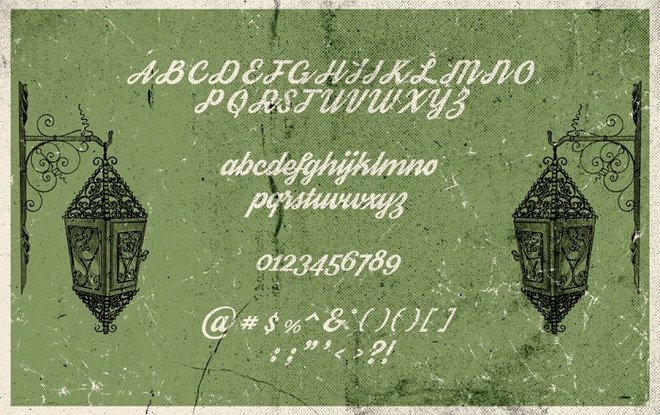
Với một Designer chuyên nghiệp, đây là 9 font chữ chẳng thể bỏ qua
Designer giờ đã trở thành một ngành nghề không còn xa lạ. Tuy nhiên, sở hữu những công cụ tốt - ở đây là font chữ - sẽ giúp các sản phẩm của họ vượt trội hơn so với phần còn lại.
Trong thời đại mọi thứ đều sử dụng công nghệ như ngày nay, việc thiết kế chữ nghệ thuật, tên các nhãn hiệu thời trang bằng máy tính đã không còn quá xa lạ.
Nhưng để tạo ra một sản phẩm mang tính thẩm mĩ và chuyên nghiệp cao, thể hiện trình độ người thiết kế quả thật không phải đơn giản. Vì thế, những bộ font chữ đẹp mắt dưới đây chính là thứ mà bất cứ ai, từ những người chỉ đơn thuần có sở thích sáng tạo cho đến "dân" thiết kế chính hiệu cũng không thể bỏ qua.
1. Elegant Gentleman
Đúng như tên gọi của nó, Gentleman cho ta thấy một sự lịch lãm, gọn gàng, và tinh tế như những quý ông khoác lên mình bộ vest đẳng cấp. Nó cũng là một sự lựa chọn hoàn hảo khi thiết kế logo, poster sang trọng. Đồng thời, đây cũng là một font chữ phù hợp để làm tiêu đề, hoặc một bài viết nào đó.
2. Glamor
Một sự lựa chọn hoàn hảo trong lĩnh vực thời trang, với bộ 24 kiểu chữ khác nhau, sang trọng và hiện đại. Chúng ta có thể thấy nó ở khắp mọi nơi, từ các poster, bìa sách cho đến những thứ có tính nghệ thuật cao như tạp chí và các trang web…
Và nếu bạn muốn thiết kế tên thương hiệu riêng, dễ nhận biết thì hãy chọn Glamor, phần còn lại hãy để "em ấy" lo…
3. GEOM
Lấy cảm hứng từ những hình học và nét kẻ đơn giản, GEOM là một bộ font chữ mang sự thoải mái và phóng khoáng.
Đây là bộ font được giám đốc nghệ thuật của São Paulo - Danilo Gusmão Silveira tạo ra, để rồi nhận được sự hưởng ứng của rất nhiều nhà thiết kế. Giới chuyên môn đánh giá, khi kết hợp font chữ trên các bìa album, tạp chí và poster phim… ta có một sản phẩm với sự sáng tạo và tính thẩm mĩ cực kì cao.
4. Samantha Script
Bộ font có phong cách nhẹ nhàng và thanh thoát, đi kèm với 1.100 chữ cái thay thế tương thích với độ dài và độ phức tạp khác nhau.
Samantha Script cho phép bạn tùy chỉnh giao diện của phông chữ theo nhu cầu để có thể tạo ra được hiệu quả tốt nhất. Có lẽ, đây là bộ font cực kỳ phù hợp để làm quote "deep".
5. Futuracha
Được mệnh danh là font chữ có thể tự tiến hóa, Futuracha đã làm mưa làm gió khắp các diễn đàn thiết kế.
Ngoài ra, nó cũng nổi bật nhờ cái tên khá... dễ thương: ghép từ 2 chữ cái "future" và "cucaracha" (nghĩa là con Gián trong tiếng Tây Ban Nha).
Font chữ tự tiến hóa đầy nghệ thuật
6. Streetwear
Nếu bạn đang muốn có một font chữ mang hướng cổ điển vintage và pha lẫn chút bụi bặm, thì Streetwear chính là thứ mà bạn đang tìm kiếm.
Với thiết kế được lấy cảm hứng từ thập niên 60 và 70, bạn có thể nhìn thấy nó ở các áo phông, các chiếc túi hàng hiệu, cũng như nhiều logo và poster trên đường phố.
7. Carioca
Khác với các font chữ khác, Carioca là một font chữ cực kì vui tươi do 2 nhà thiết kế Tano Veron và Yai Salinas sáng tạo.
Với sự thay đổi về màu sắc trong từng chữ cái, Carioca sẽ là một phần không thể thiếu khi bạn dự định thiết kế áp phích đồ họa hay các bìa album yêu cầu tính sáng tạo cao.
8. Bauru
Được truyền cảm hứng từ những ca khúc nhạc Jazz và Soul, Bauru là đứa con tinh thần của nhà thiết kế Pier Paolo. Đây chắc chắn sẽ là font chữ đầu tiên bạn nghĩ đến khi chuẩn bị thiết kế cho những phòng trà, hay các thương hiệu liên quan đến âm nhạc.
9. Minna Drop
"Cô nàng" Minna này có thể giúp cho bất kì bản thiết kế nào trở nên cực kì thú vị, xen một chút tinh nghịch và đặc biệt thu hút các em nhỏ.
Nếu bạn để Minna "nhảy nhót" trên các bìa sách thiếu nhi thì đó chính là một sự kết rất hợp tuyệt vời đó!